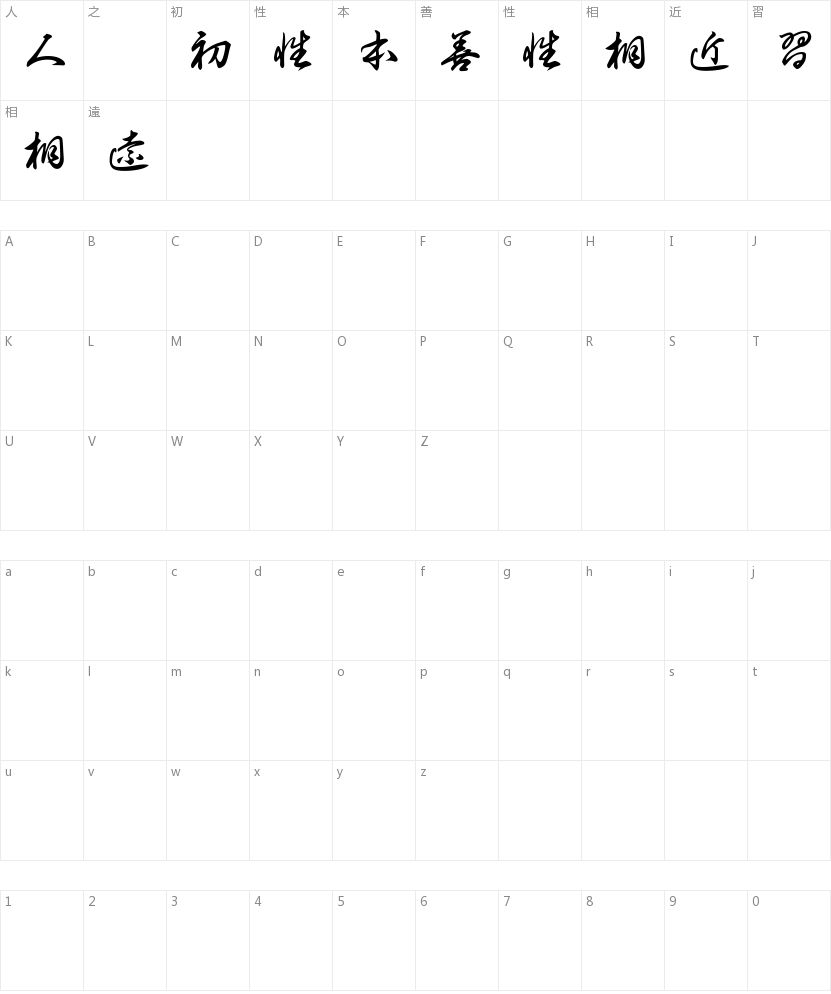
白舟草书教汉字体是一款中文字体,它继承了传统楷书的精髓,但又有所创新,具有浓郁的民族特色。白舟草书教汉字体的字体特点:字形简洁、笔画均匀,笔画流畅,线条优美,结构紧凑,笔划精细,构成比例协调,有较强的美感,字体结构精致,表现力强,能满足不同的应用需求。文件名:BaiZhouCaoShuJiaoHan-1.ttf
白舟草书教汉是一款非常不错的手写艺术字体,具有很好的视觉感,适合于文化类的宣传设计、商业类品牌的广告和产品包装设计以及个性化文字排版等较多场景。